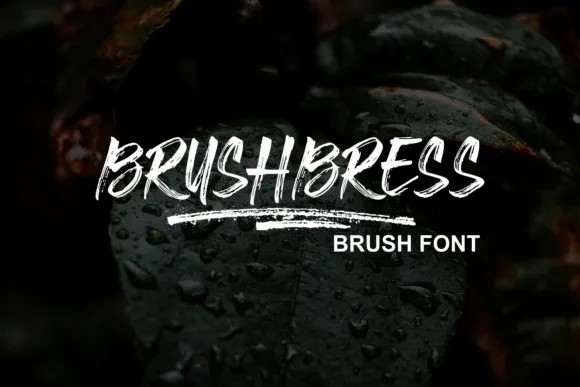
Brushbress Font – Download Grátis
A Brushbress Font é uma elegante escolha para projetos que exigem personalidade e sofisticação moderna. Criada pelo designer zamjump, essa fonte tem uma atmosfera casual e autêntica, ideal tanto para aplicativos de negócios quanto para plataformas sociais como Instagram. Sujeitável a vários tipos de projetos, desde as marcas empresariais até os blogs ou portfolios pessoais, e inclusive se adequando à moda, esportes, entretenimento cinematográfico e fotográfico, além de hobbies diversos. A particularidade desta fonte é seu sistema PUA (Unicode) encodado, o que lhe dá acesso a todos os símbolos e aberturas. Isso significa que você pode explorar todas as cores da sua criatividade sem limites, garantindo sempre uma aparição única e imprevisível em seus projetos. Seja para um projeto de branding sofisticado ou uma postagem Instagram descontraída, a Brushbress se adaptará perfeitamente.